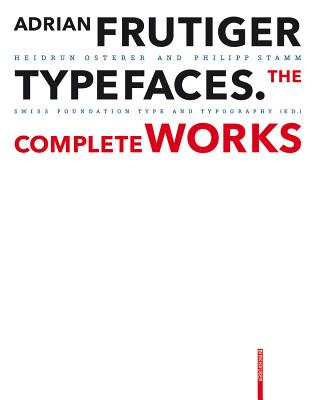
Das internationale Schriftschaffen nach 1950 wurde ma???geblich gepr???gt vom Schweizer Adrian Frutiger. Sein Schriftprogramm Univers und die zum ISO-Standard erkl???rte, maschinenlesbare Schrift OCR-B sind ebenso Meilensteine wie die zur Frutiger weiterentwickelte Schrift der Pariser Flugh???fen - ein Qualit???tsstandard f???r Signalisationsschriften. Mit den Corporate Types pr???gte er Firmenauftritte wie den der japanischen Kosmetiklinie Shiseido. Insgesamt entstanden rund 50 Schriften, darunter Ondine , M?? ...